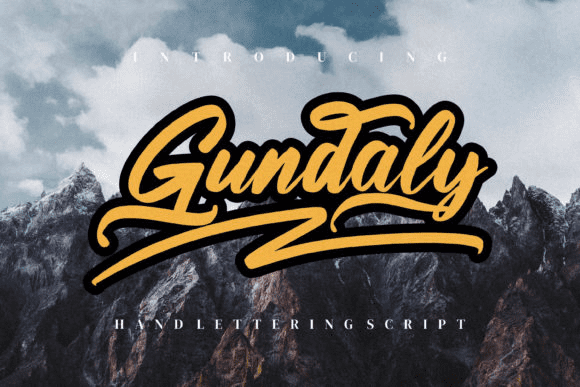
Название: Gundaly Font
Гундали - уникальный рукописный шрифт.
Чистый и немного причудливый, этот шрифт идеально подходит для всех ваших логотипов, брендинга, социальных сетей и хитрых DIY проектов.